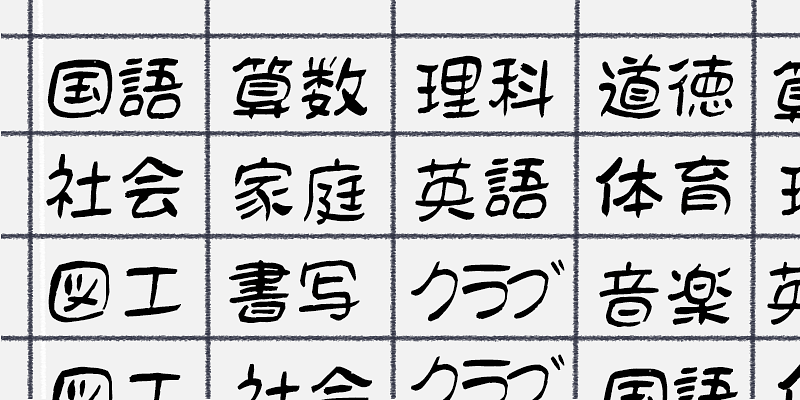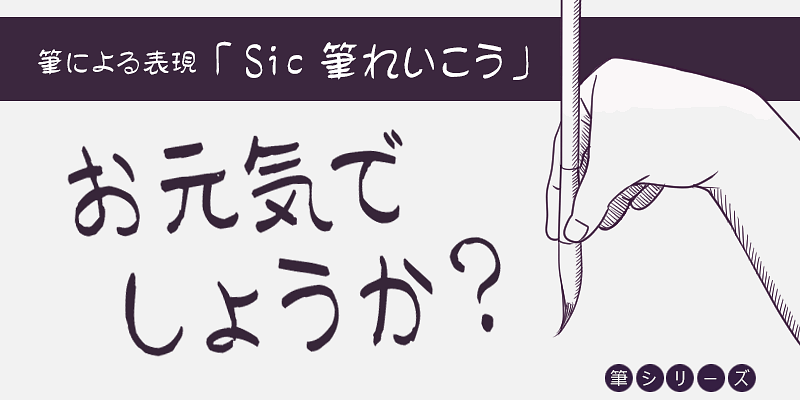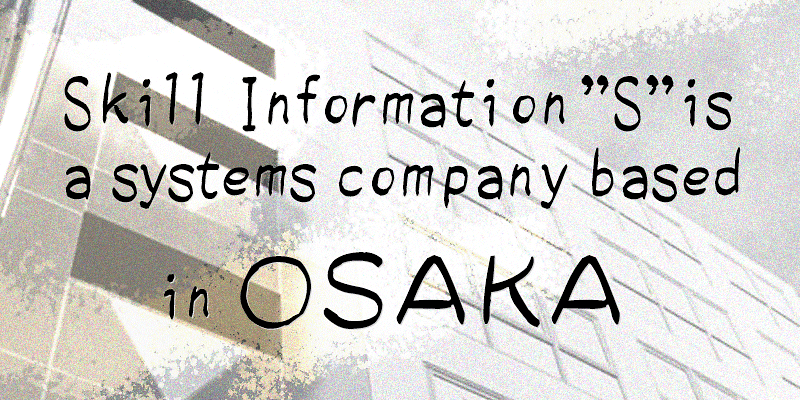
「故・鈴木竹治氏が手掛けたフォントは、レタリングからビットマップ、ワープロ、毛筆書体まで幅広い経験を基に生み出されました。特に「ヨコ組のときストレスの少ないゴシック体」を追求し、可読性に優れたデザインが Windows 標準搭載フォント〈メイリオ〉へと発展しました。
その書体デザインの多様性は、温かみのある手書き筆文字書体・基本書体にとどまらず、広くゴシック体やデザイン書体にまで及んでいます。広告や映像、デジタルメディアなどを含む幅広い用途にご利用いただけます。オリジナルの楽しさを感じられるフォントを提供し、多くの人に親しまれています。」
スキルインフォメーションズはヘルスケア関係のソフトウエア開発を中心とする会社ですが、2007 年にフォントシステムの開発を手掛けていたテクノアドバンス社と事業提携し、フォント事業部を開設しました。